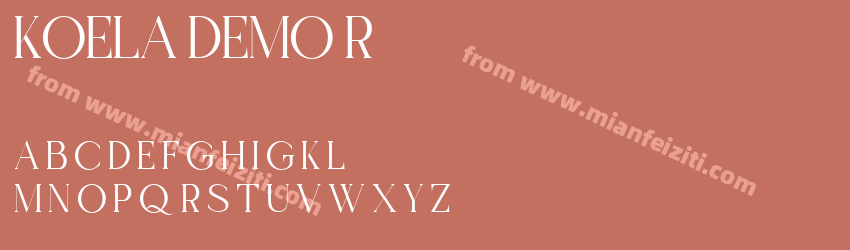
KOELA DEMO Regular
字体名称: KOELA DEMO Regular
KOELA DEMO Regular预览图1
KOELA DEMO Regular预览图2
KOELA DEMO Regular字体映射图
本款“KOELA DEMO Regular”是一款书写很新颖的字体,字体大方,适合各种设计作品使用!欢迎下载!